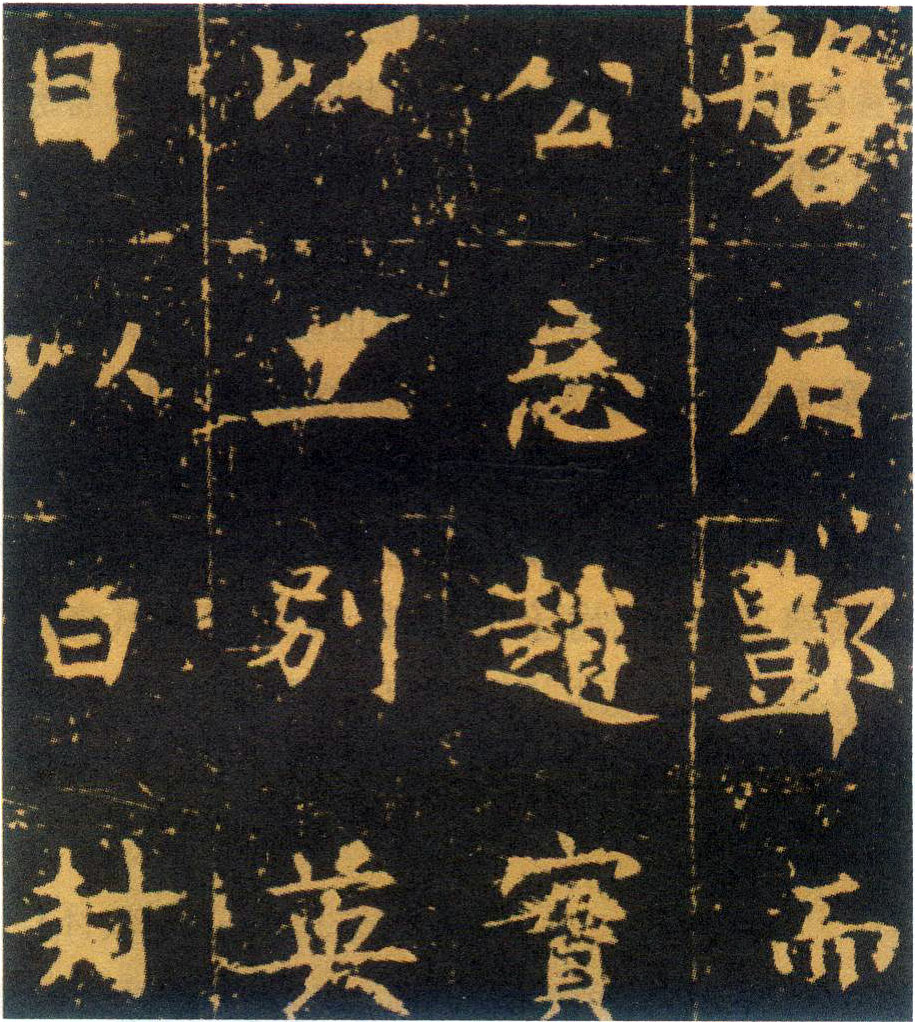
赵模
赵模简介
赵模,太宗时翰林供奉拓书人,太子右监门府铠曹参军。正书字画甚工。《宣和书谱》载“模喜书,工临仿。始习羲献,学集成《千文》,其合处不减怀仁,然古劲则不迨。”唐太宗在喜获《兰亭》之后,曾命赵模与韩道政、冯承素、诸葛贞四人各响拓数本,赐给皇太子、诸王与近臣。《宣和书谱》称宋内府曾收有《模集千字文》,然传世书迹仅见《高士廉茔兆记》。
《高士廉茔兆记》,许敬宗撰,赵模楷书,永徽六年(655年)立石。其书方整秀逸,明代学者赵崡《石墨镌华》有“大类欧、虞”之评,至刘熙载《艺概》则谓其精熟遒逸,比肩王知敬。康有为《广艺舟双楫》中对赵模亦有较高评价:“赵模之《兰陵公主碑》、《高士廉茔兆记》、《崔敦礼碑》体皆相近,皆清朗爽劲,与欧虞近者也。”,康氏谓《兰陵公主碑》、《崔敦礼碑》出自赵模手笔,虽为有显误,然亦可见其对赵模之推重。
赵模《高士廉茔兆记》(局部) 655年